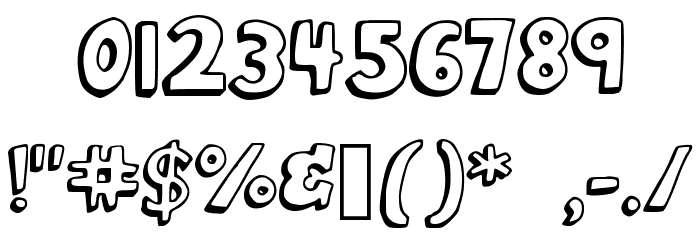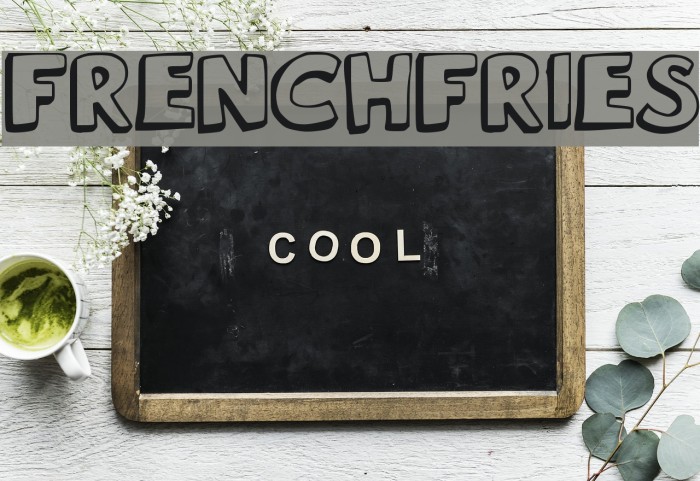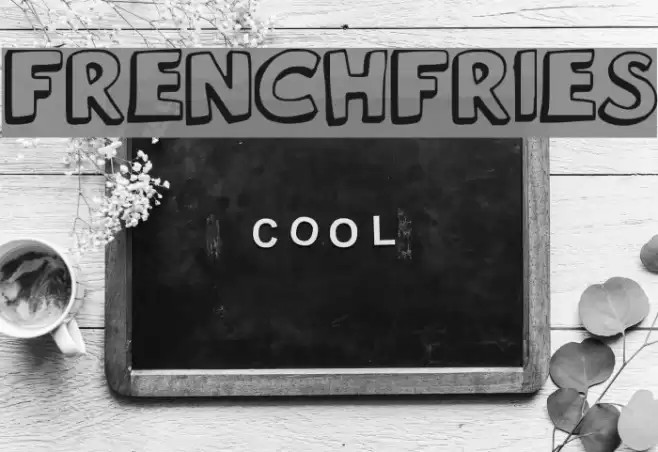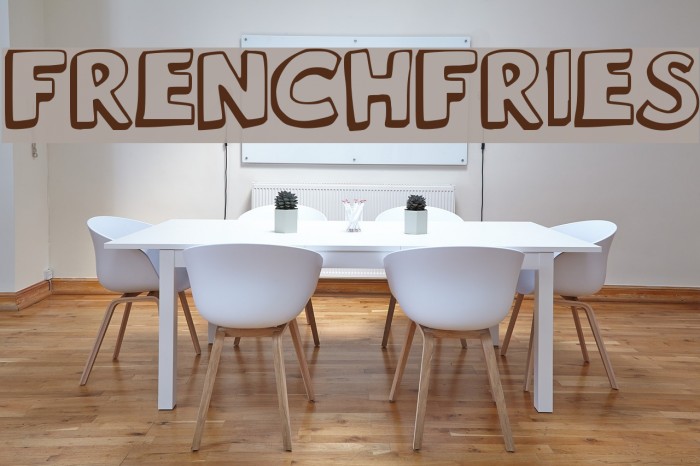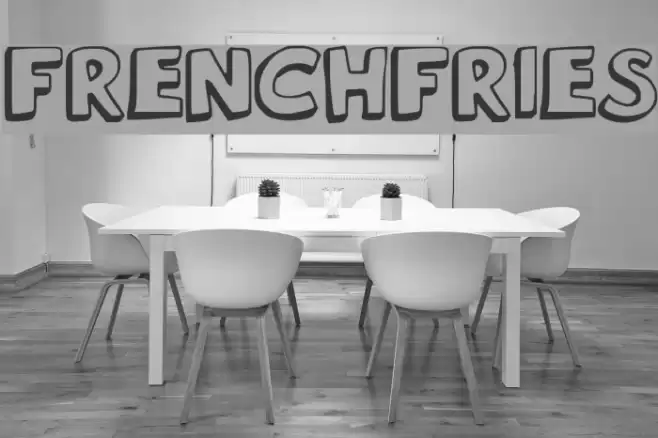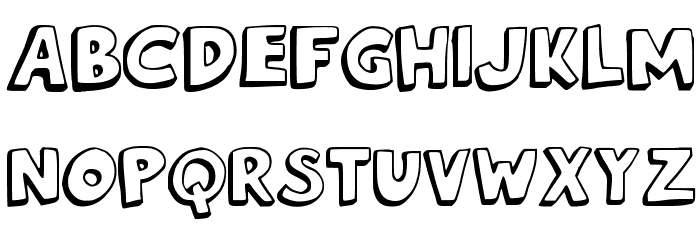
French_Fries Font
| Stil general | Playful, Cartoonish |
| Proiecte propuse | Perfect for children's books, comic strips, playful branding, party invitations, and any project needing a fun, lively touch. |